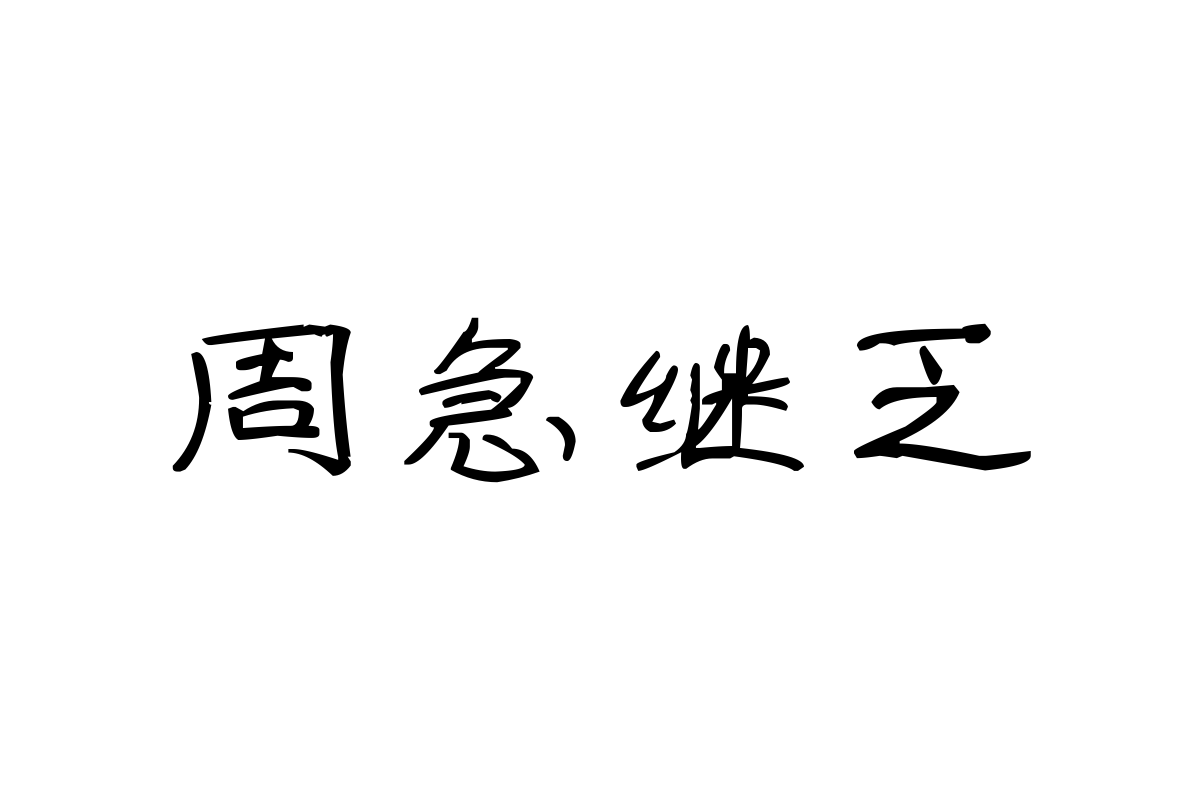
汉标秀丽芳华体是一款具有独特魅力的字体,它采用了优美的线条和优雅的笔画,使得整体看起来既美观又大方。这款字体的设计灵感来自于自然之美,通过巧妙的布局和结构,展现出了大自然的和谐与美丽。
汉标秀丽芳华体的笔画流畅而有力,每一个笔画都经过精心设计,使得整体看起来既流畅又富有力量感。它的字形结构紧凑而均衡,无论是在书写还是阅读时,都能够给人带来舒适的感觉。
此外,汉标秀丽芳华体还注重细节的处理,每个字符的形状都经过精心雕琢,使得整体看起来既精致又典雅。它的字体大小适中,适合各种场合使用,无论是用于印刷品、海报还是网页设计,都能够展现出其独特的魅力。
总的来说,汉标秀丽芳华体是一款具有独特韵味和美感的字体,它不仅能够提升文字的可读性,还能够给视觉带来愉悦的感受。无论是用于个人作品还是商业用途,都值得一试。